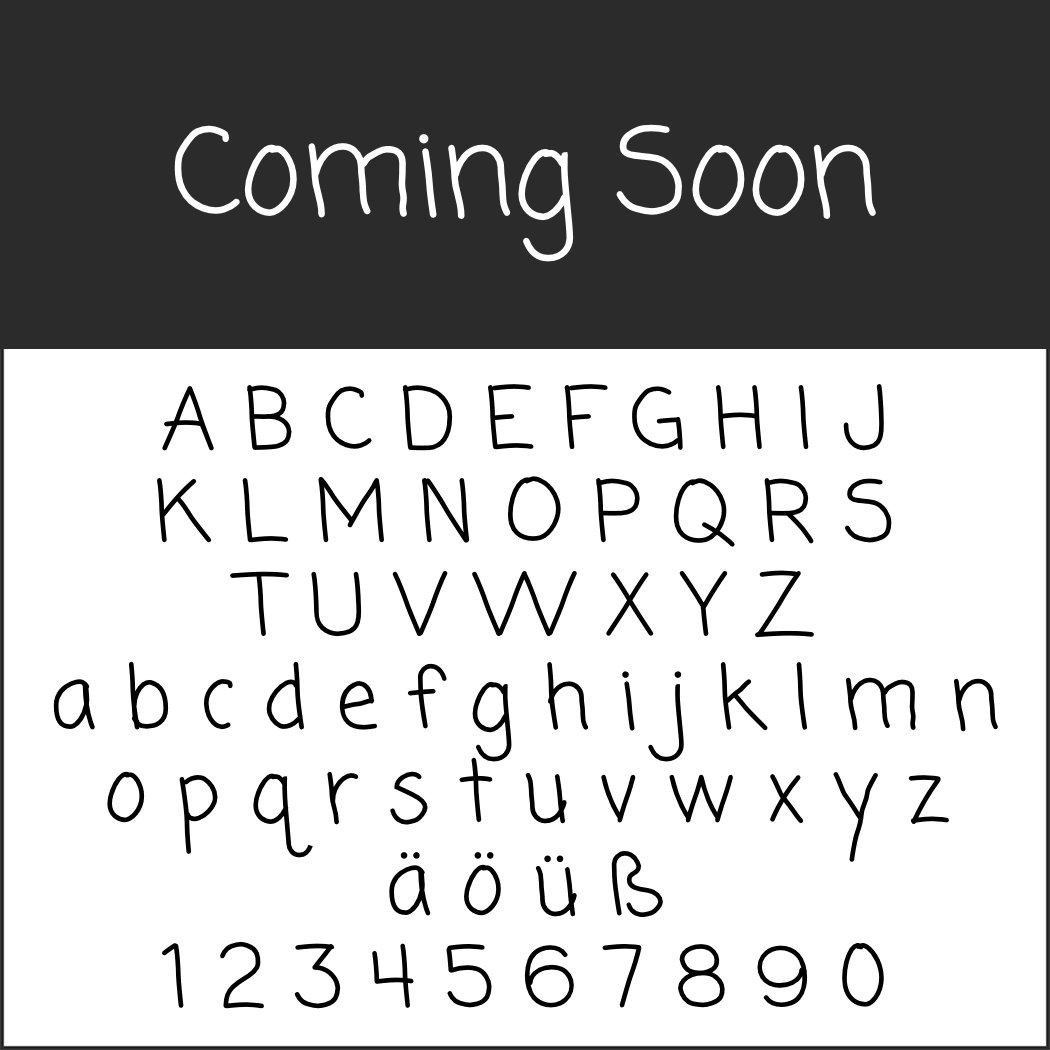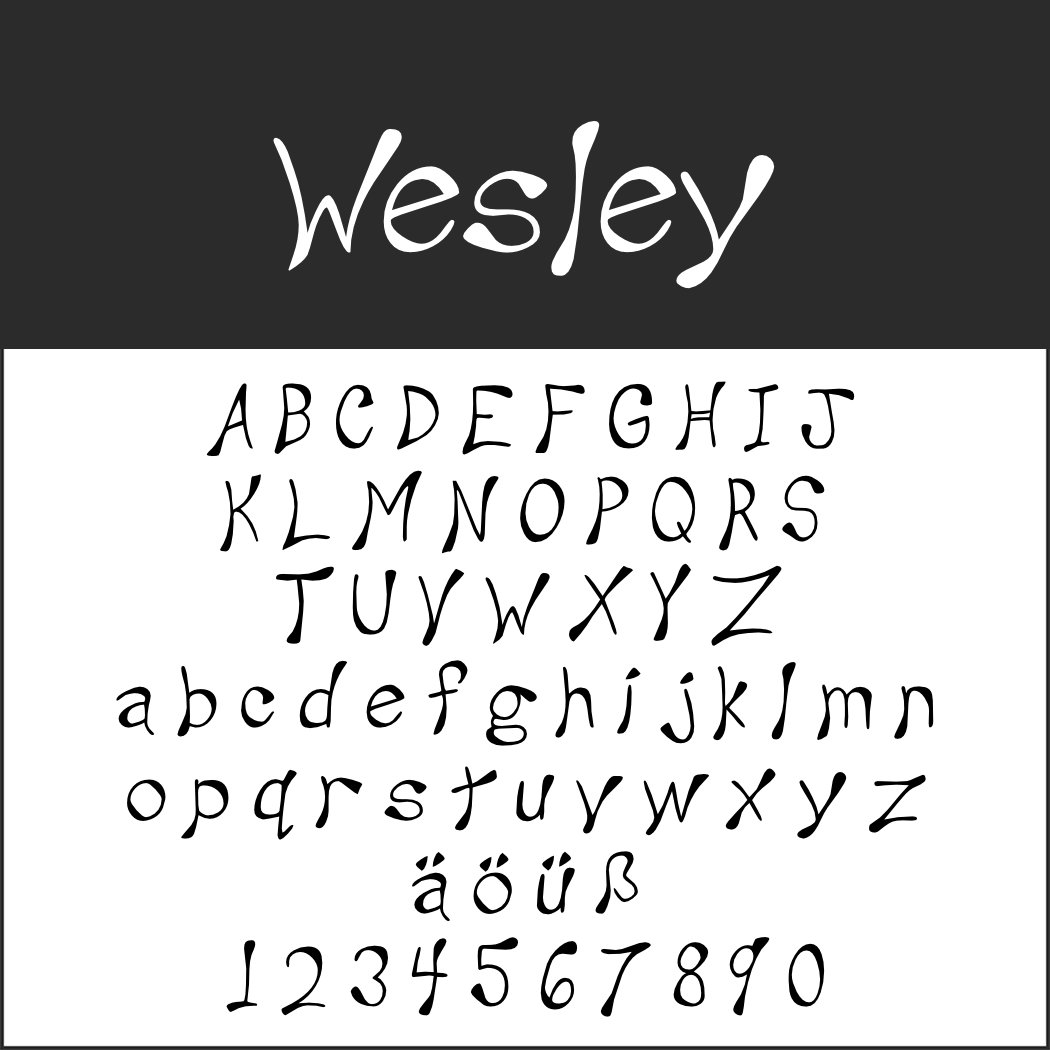
Was handwerklich und mit viel Liebe hergestellt wird, benötigt auch eine entsprechende Präsentation. Selbst geschriebene Schilder zum Beispiel liefern den passenden Rahmen und weisen auf eine Produktion mit kleiner Stückzahl hin. Man muss allerdings nicht unbedingt selbst zum Stift greifen. Im Internet finden sich einige Schriftarten Handschrift, die den gleichen Effekt erzielen.
Wir haben uns für diese Auswahl auf Fonts beschränkt, die auf echten Handschriften basieren oder diese imitieren. Das heißt, sie weisen alle kleine Unregelmäßigkeiten auf. Wenn Sie auf der Suche nach perfekten Script-Fonts sind, finden Sie am Ende des Artikels weiterführende Links zu entsprechenden Gratis-Schriftarten.
Schriftarten Handschrift – gratis und kommerziell nutzbar
Schriftarten Handschrift: AmaticAmatic
Sieht aus wie von Hand geschrieben – und ist es auch. Optimiert für den Gebrauch auf Bildschirmen funktioniert Amatic aber auch gedruckt.
• Design: Vernon Adams
Schriftarten Handschrift: 5 Years Old5 Years Old
Der französische Designer digitalisierte hier die Handschrift seines fünfjährigen Sohnes. Sie eignet sich deshalb besonders gut bei Angeboten für Kinder.
Handschriftliche Schriftart: AvocadoAvocado
Nicht jeder kann mit einer Feder so souverän umgehen. Dennoch hat der Designer die Vorlage von Hand geschrieben. Mit Hilfe eines Grafikprogramms erhielt Avocado den letzten kalligraphischen Schliff.
Handschriftlicher Font: Cheveuxdange
Bei Cheveuxdange haben wir einen Kreide-auf-Tafel-Effekt mit mehrfachen Linien. Die Wirkung zeigt sich in ihrer ganzen Pracht besonders auf Plakaten.
Schriftart Handschrift: Coming soonComing Soon
Mit diesem Font setzte der Designer aus Wisconsin die Schulmädchenhandschrift seiner Mutter um. Besonders gut passt sie bei allen von Hand hergestellten Produkten.
Schriftarten Handschrift: GemelliGemelli
Der Designer hat seine eigene Handschrift digitalisiert und nach seiner Lieblingspasta benannt.
Handgeschrieben Schriftart: Huxtable
Eine Serifenschrift, die durch die Unregelmäßigkeit der Buchstaben ihren Charme des Handgeschriebenen erhält.
Handschriftlicher Font: HVD Steinzeit
Was Schülern so an Beschäftigungen einfällt, wenn sie sich im Unterricht langweilen. Daran erinnert dieser handgezeichnete 3D-Font.
Schriftart Handschrift: LaviLavi
Wie mit dickem Filzstift geschrieben wirkt Lavi trotz seiner Ecken sehr harmonisch.
Handgeschriebene Schrift: Popcorn Mountain
Mal eben schnell notiert – so sieht Popcorn Mountain aus. Und so wie das namengebende Knabberzeug fürs Kino sorgt auch dieser Font bei passendem Einsatz für gute Laune.
Schriftart Handschrift: Razor Keen
Gedacht ist Razor Keen als gruselige Schrift – beispielsweise für Halloween. Sie kann aber auch dann zur Anwendung kommen, wenn eine Schrift unbeholfen wirken soll.
Schriftart: WesleyWesley
Eigenwillig und unbekümmert präsentiert sich Wesley, das sich damit vor allem für unkonventionelle Produkte eignet.